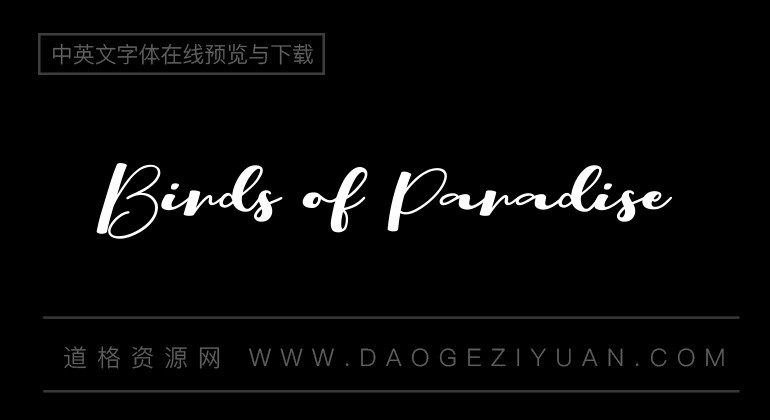
Birds of Paradise 是一款由Font Diner创作的英文手写字体,它拥有活泼的线条,每一个字母都充满了生机。它由一系列曲线和笔画组成,以及一些折线和圆弧组成,使它看起来很有趣。它有一个明亮的外观,适合用于卡片,海报和标题。它也有一些可爱的小细节,比如细长的字母,小点和线条,以及可爱的结尾符号,使它看起来更加有趣。内容介绍
Birds of Paradise是一款非常不错的手写艺术字体,具有很好的视觉感,适合于文化类的宣传设计、商业类品牌的广告和产品包装设计以及个性化文字排版等较多场景。